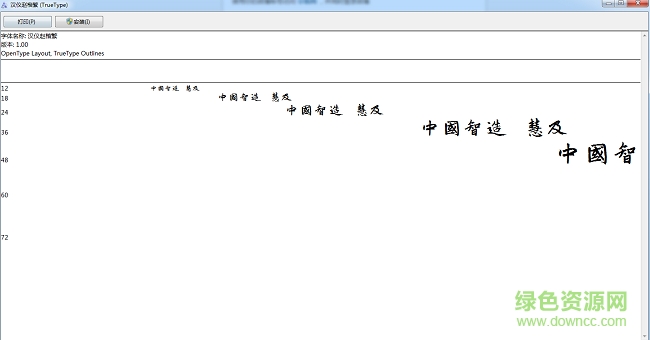
hyc4gf字體是一款英氣逼人的漢儀繁體字體,字形瀟灑美觀,結(jié)構(gòu)疏密得宜,整體挺秀俊逸,藝術(shù)性強(qiáng),用在廣告字體或海報字體都不錯,需要的朋友快來綠色資源網(wǎng)下載吧!
小楷,顧名思義,是楷書之小者,創(chuàng)始于三國魏時的鐘繇。他原是位隸書最杰出的權(quán)威大家,所作楷書的筆意,亦脫胎于漢隸,筆勢恍如飛鴻戲海,極生動之致。惟結(jié)體寬扁,橫畫長而直畫短,仍存隸分的遺意,然已備盡楷法,實(shí)為正書之祖。